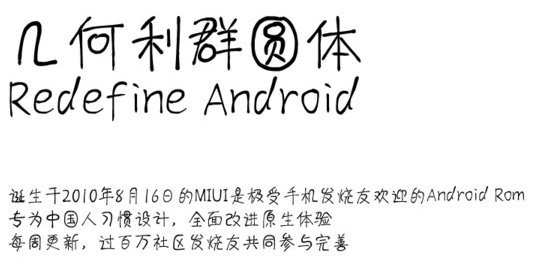
幾何利群圓體是一款更加細(xì)膩柔潤的葉利群幾何字體,結(jié)合幾何字體和圓體字體的特色,給用戶帶來別樣的視覺體驗(yàn),更利于大家的閱讀和設(shè)計(jì)使用,綠色資源網(wǎng)誠意推薦!
“方圓有度,端莊圓潤”,這就是利群圓體! 幾何字體是一類寄托著夢(mèng)想和情懷的字體,是一類讓漢字筆畫更加簡潔有規(guī)律的字體,是一類有利于閱讀和教學(xué)的字體!
幾何利群圓體與幾何圓體、立群幾何極簡體均不相似,但藝術(shù)效果都有很不錯(cuò)的呈現(xiàn),讓文字顯得更加柔軟秀氣,給你的平面設(shè)計(jì)、包裝設(shè)計(jì)增加獨(dú)特美感。